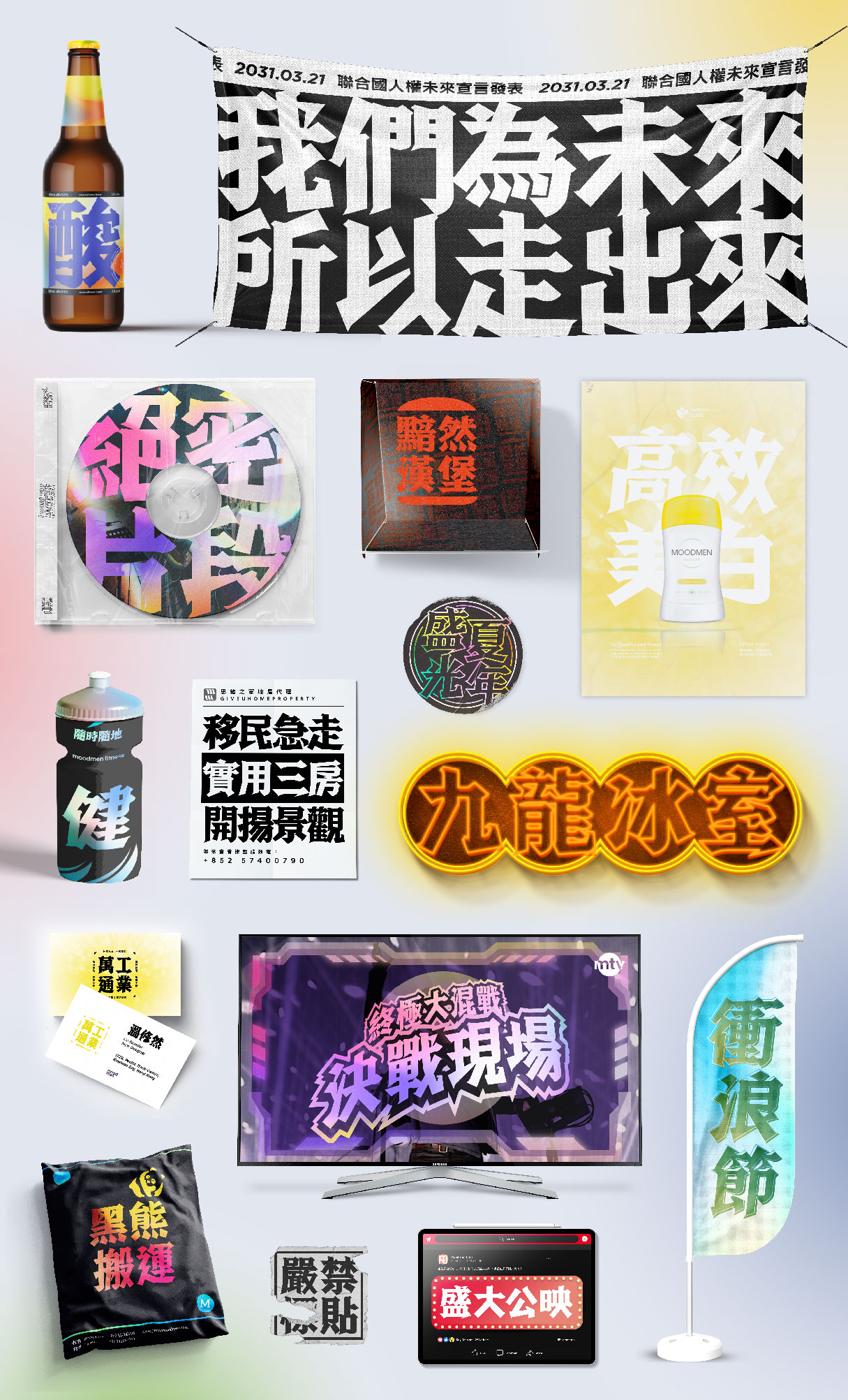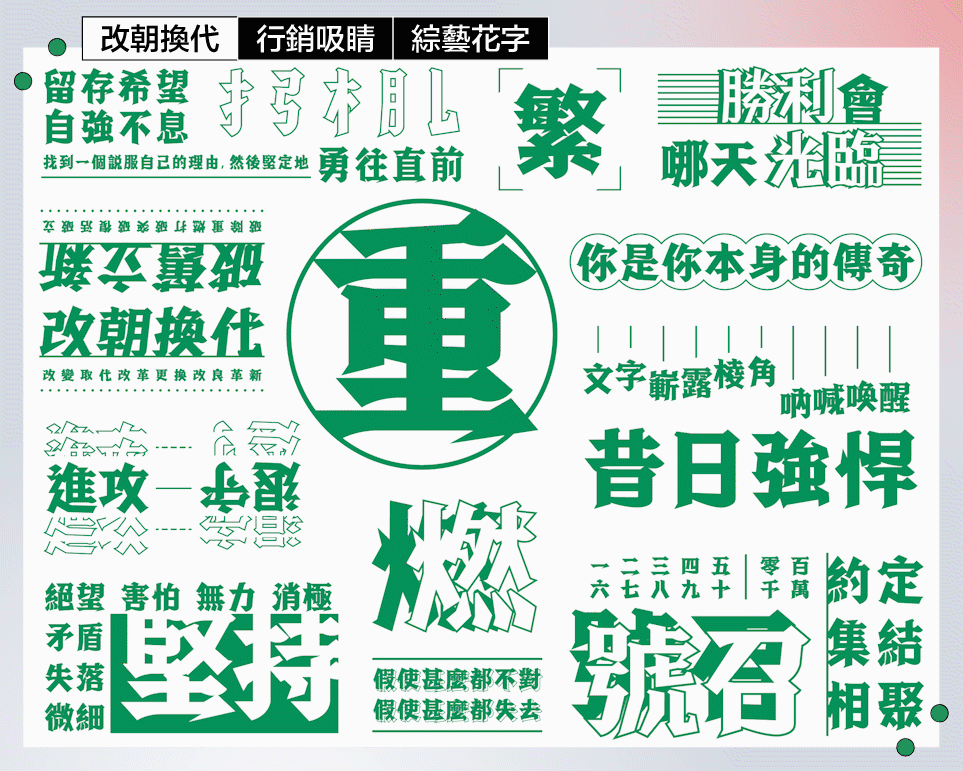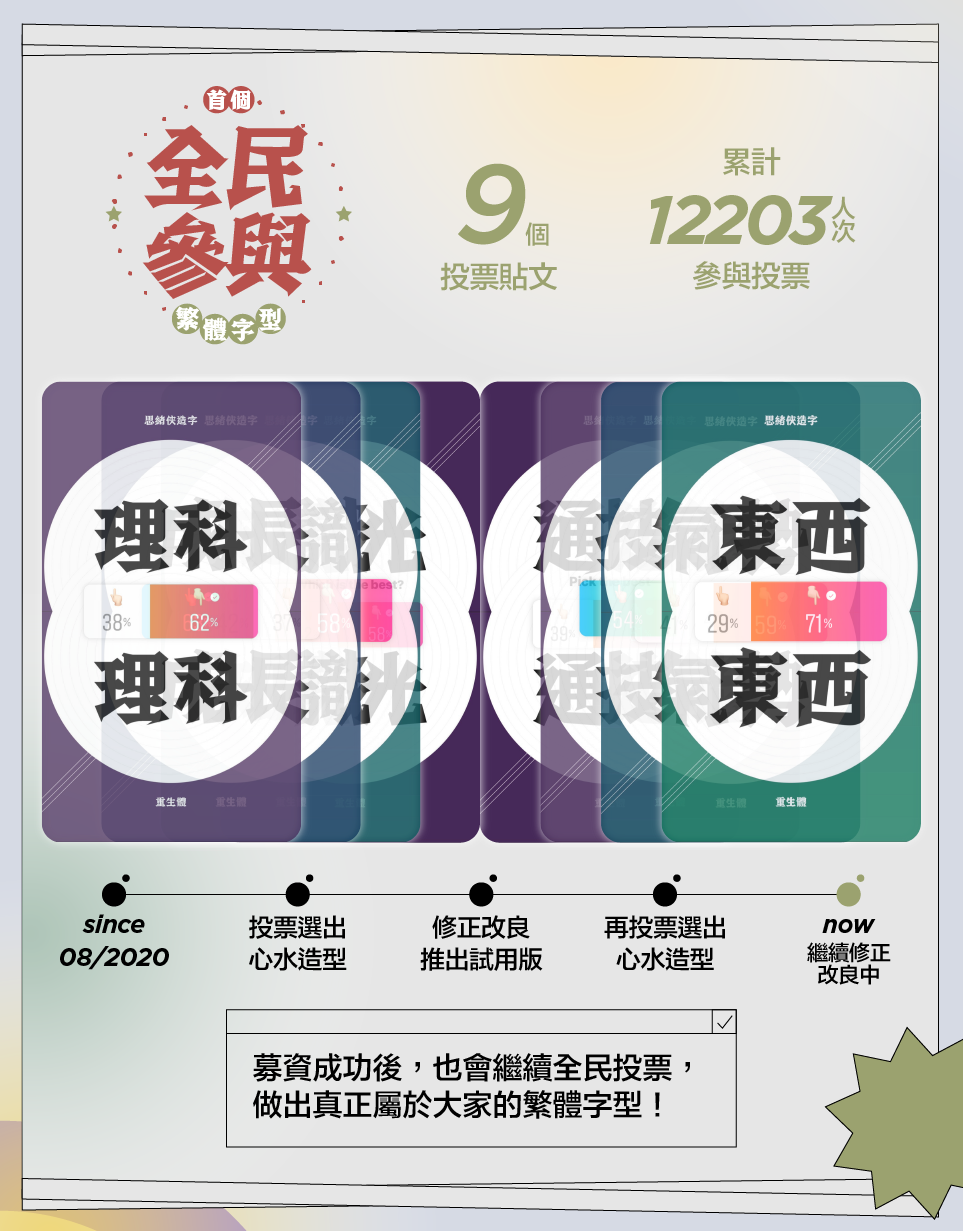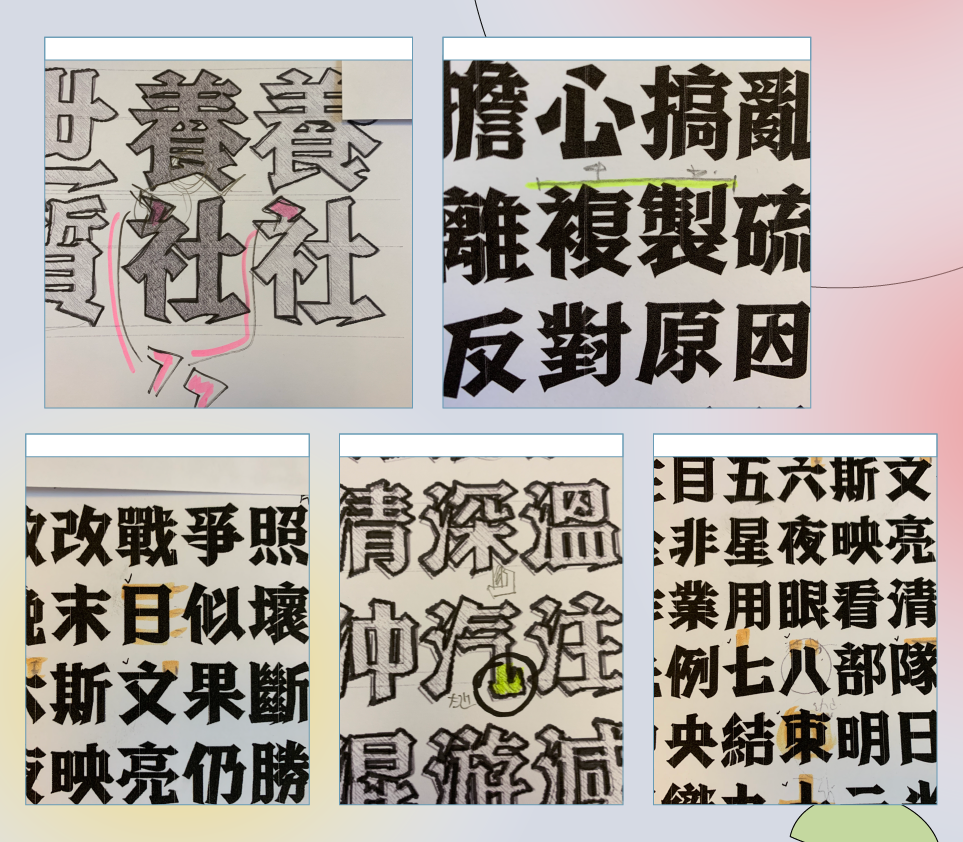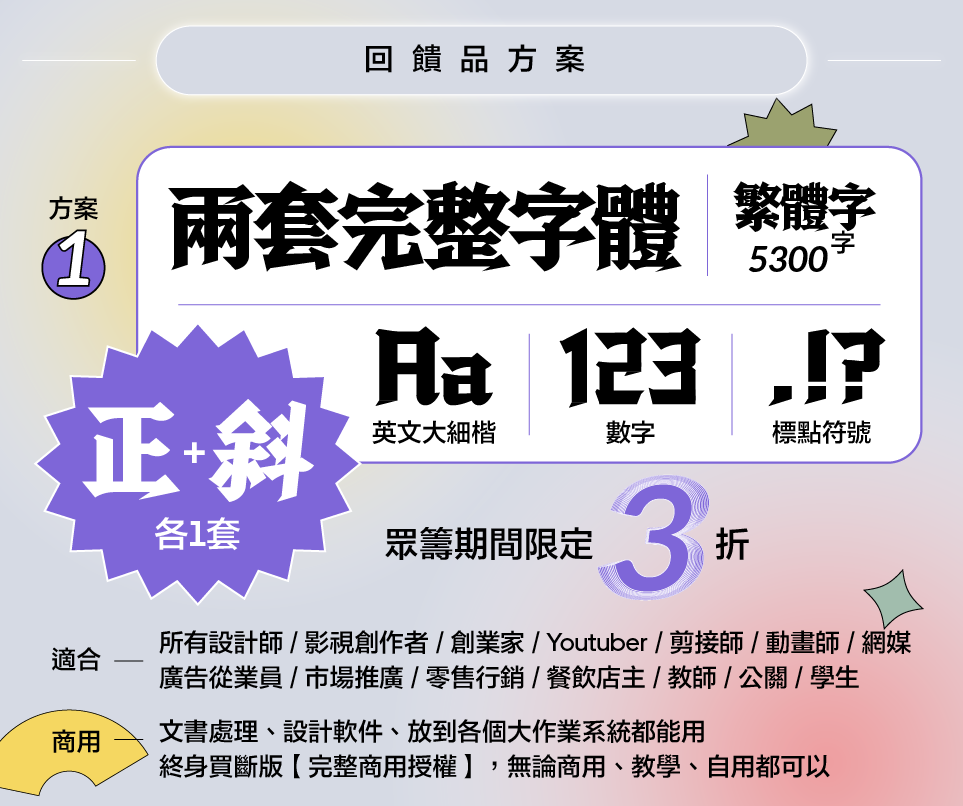
思緒重生體為思緒俠造字第一個字體項目,於2022年1月發起為期兩個月的眾籌募資,並成功募資港幣101萬(353萬台幣),會於同年12月交付5300字元版本,現時全力製作中。
在日新月異的時代洪流之中,每一個人、每一件物品彷佛都置身於記憶和遺忘之間的對奕。舊物被淘汰似乎是社會上的自然法則,但在時興復古的今天,有誰又能全盤否定它們的價值?舊事物的可愛之處,在於它從歲月之中沉澱下來的獨特韻味,不單構成了我們對這個地方的喜愛和熟悉感,同時亦為城市賦予了生命力。文化往往是能豐富一整座城市的肥料,而且正是有著這些林林總總的事物,才能堆疊出讓城市確實地文明的深度。
舊時的景物往往最具韻味,它不但是屬於香港人的回憶,更是給予這個城市個性和價值的重要角色。手雕麻雀、戲棚、點心車⋯⋯你又數得出多少曾經熟悉的事物?又有多少已經在腦海中模糊了輪廓?保育固然重要,但純粹地留住這些文化似乎還未足夠,而它們總會在某一天失傳。正因為不甘失去,香港一些日漸式微的傳統工業都嘗試以舊物為本,保留原有基礎的同時也為它注入新元素,讓它們不論軀殼還是靈魂都得以延續。
那麼,香港的文字應該傳承下去嗎?如果沒有人繼續造字,它會成為社會下一個淘汰的對象嗎?
由陳靖軒創立的思緒俠造字,自 2019 年至今透過社交平台上的字體設計作品、不同造字產品,一直致力於推廣繁體字的設計。然而,只是讓人意識到有字體設計的存在也顯然未夠,我們仍不斷在字體創作上尋求突破,才促成了思緒重生體這套完整中文字型的誕生。處於每秒都在變化的世代中,比起一味的懷舊,我們更希望在傳統的根柢上創造出與時俱進、更甚是引領潮流的一套字體。
生於複雜多變的時代中,每天都要面對著不同的變數,身邊一些珍貴而美好的事物都逐一消失。我們似乎已經對這些所謂的常態感到麻木,甚至開始默默地接受。有人說,世界上所有美好事物都會有一個期限;但我們卻不甘失去,希望可以藉著字體設計,加入一些本地獨有的人文面貌,將香港的靈魂重生。
能剛則剛,能柔則柔,做到互補之餘又恰當好處, 這就是詠春的智慧;上海理髮廳剃刀的鋒利,乾淨俐落,是對於自我肯定的表現;舞獅動作多變而威武,盡顯氣派; 手雕麻雀的精細,展現出師傅對工業的執著和熱誠。這些傳統工業雖然面臨淘汰,便仍然堅守崗位,保持應有的專業態度,若果重生體可以加入它們的元素,再將宋黑結合,我相信這將會是一套能夠延續香港靈魂的繁體字。
設計上,重生體凌厲而細緻,務求做到藝術性與可讀性之間的平衡。無論作為文案標題、招牌設計、商品包裝甚或張貼告示,重生體都能盡展其獨一無二的字體個性,為其文字內容施加張力之餘,也打破傳統字型沉實呆板的印象。尤其是在資訊爆棚的現代城市中,更需一款搶眼獨特的標題字體,留住人們的視線之後,延續他們閱讀內文的興趣。
在我們身處的後印刷時代中,印刷術極其普及的同時,電子媒介亦已融入大家的日常。重生體作為一套回應時代潮流的字體,便在字型設計的架構上揉合了印刷品慣用的「宋」和電子屏幕上常見的「黑」,讓字體靈活地配合各種應用,應對每息間千變萬化的都市。
在潮流上創新之外,重生體也希望透過宋黑結合做到文化上的傳承。宋體(明體)的歷史可追溯至古時的活字印刷,它有為了方便雕刻而加粗的豎筆和標誌性的三角裝飾,絕對稱得上傳統美學的代表。另一邊廂,黑體則是受西方字體影響才衍生出的無襯線字型,因為筆劃粗幼一致、簡明清晰,故其可塑性高也更具時代感。
重生體保留了宋體的筆劃頭尾裝飾,卻又加入了黑體的硬度、統一了橫豎筆的粗幼,從而達至宋與黑、新與舊的融合。這樣的設計除了能讓字型更獨特出眾,也令字型能廣泛應用於不同媒體、介面,呼應時代的需求。這樣一來,重生體有望能切合「加入新元素,將傳統美學轉化成潮流」這一宗旨,將固有的人文精神流傳到下一代。
重生體的橫筆是其宋體特性最濃厚的地方:它有鋼筆般銳利的開首,也有像雪糕筒的尾端裝飾,而當整個字以橫筆作結時,更有像鋤頭作出還擊的回勾。相反地,「口」字部的底部橫筆則摒棄了鋼筆和雪糕筒等裝飾換成有輕微弧度、逐漸向左收窄的回筆。如此一來,相對柔和的收筆除了能緩和視覺疲勞,也為這剛強的字體添加一點溫柔。
在其他細節設計上,重生體也十分講究,正如看似隨意的每一「點」,在不同情況下也會有各自的形狀和調整。首先在一般狀況下,點的設計會呈菱形狀並帶有尖銳的尾巴; 其次,當點作為字元尾筆或重複使用時(如在「灬」「糹」等部件中),它會順應筆劃走向調整重心並向外擴展,展現猶如書法的氣派。至於在空間不足的時候,點則會縮減至兩端收細的箭頭造型,修補正負空間的比例平衡。
此外,重生體在撇捺交叉出現的「又」字部中,會在兩筆重疊的地方隱藏一個曲折處。除了有助校正粗幼和重心,這種處理手法也讓筆劃較符合視覺上的直線,使其更順眼自然。
思緒重生體在較早前推出的試用版反應不俗,我們非常榮幸地得到各個界別的創作者支持,將重生體帶入不同作品中,當中包括由樂隊 Kolor 主理的 Ohm…cafe 內其中一個霓虹燈裝飾「醉.醒」,另外香港 Youtube channel「非實力派」亦在影片封面中使用了重生體。除了本地創作人之外,台灣餐廳「門常開合作社」的主視覺設計亦率先試用了字體。而最令我們團隊喜出望外的絕對是設計師 iohn.choi 將重生體放進作品內,並帶到了達明一派演唱會的大舞台上,我們希望藉此會有更多人認識和使用思緒重生體。
為了打造一套真正屬於香港的字體,我們進行了首個全民參與的繁體字設計項目,在埋頭苦思字體設計的同時,也希望凝聚所有熱愛繁體字的人一同參與字體的調整。我們於 2021 年 10 月推出試用版前進行了第一輪公投,挑選出部份詞彙,以同一個字、兩款不同設計的方式,讓網民進行二選一投票。我們亦跟據投票結果,在試用版出貨前作出修改,讓用家可以試用由全民參與改良所得出的字體,並回饋意見。
正正因為繁體字是大家所珍惜的,所喜愛的,才會特別著緊。我們知道當中每一筆一劃的設計都是使用者所關注的,也願意讓用家成為字體設計企劃的一份子。往後的日子在完整版還未釋出前,我們還會繼續以全民投票方式決定筆劃造型,務求盡善盡美。
如果時間是金錢的話,那麼設計繁體字便是一件非常奢侈的事。就算只以字數衡量,繁體中文的字庫已遠超於英文等語言,而且繁體字結構複雜多變,當中的每一筆一劃都是設計師需要反覆思量的學問。思緒重生體經過籌備和設計的程序後,便進入修正部分,反覆改良出至少十多個版本。我們調整的準則主要為統一直橫筆的開端、減少筆劃交集、調整比例和加強字型特性。經過三百多天反覆修正,我們不斷思考著如何才能將每一隻字都調整至最大的氣派,厚厚的一堆草圖上滿載著我們團隊對重生體的執著,以及對繁體字的熱愛。
需知道創造一個新字體的工序相當繁複,而且成本龐大,但我們還是會堅持做,除了讓大眾有多一個繁體字型的選擇之外,更是為了傳承繁體字的文化,讓香港人也會為香港製造的字體而感到驕傲!
字型選擇眾多的英文字體一般只需製作約 300 個字元,相比起來,字元總數成千上萬的繁體中文便明顯較為繁複,也自然要耗費更多時間心力。跟據台灣教育部所編訂的中文字編碼庫,電腦中常用的繁體字共有 13,051 個,並可劃分為 5,401 個「最常用字」及 7,650 個「次常用字」。因此,一套完整中文字型動輒便需花上以年計的時間去完成,而這也是市面上繁體字型少之又少的主因。
據統計,1,000 個常用中文字其實已覆蓋了 92% 的書面資料,3,000 個常用字更能達到 99% 的覆蓋率。早前,思緒重生體已從最常用字中精選了「表演」、「勝利」等 1,000 個「超常用字」作為試用版率先釋出。在眾籌第一階段中我們會加入「搜索」、「巔跛」等補至一共 5,300 個字元,當中亦包括「冇乜」、「佢哋」等香港常見字。雖然 5,300 字已能應付近乎全部設計上所需的文字,然而也有唏噓的「唏」、叱咤的「咤」等不屬最常用字、卻偶爾會用上的缺字,仍有待眾籌第二階段的 8,800 字去解鎖。要讓思緒重生體成為一套完整的字體,我們需要你的支持, 讓世界知道香港製造的字體是有市場、有品質及有價值的。
【回饋方案一】為是次眾籌的主打,我們將會提供正斜體各一套的思緒重生體。作為一套香港製造的繁體字,除了英文大細階、數字和基本的標點符號之外,重點一提的是,在 5,300 個繁體字當中也包括了一些香港口語字(例如「佢」、「啲」、「咁」、「嗰」、「係」等) 方便香港人使用。正體方面我們著手調整字體結構的比例,而斜體我們亦反覆比對不同斜度,最後選出了最為適合的 6°,希望可以節省使用者自行調整的時間。為了回饋支持者,整套字體於眾籌期間將會以限定 3 折出售!
【回饋方案二】思緒重生體將會首次出售眾籌限定的麻雀套裝。麻雀以藍黃橙三色設計,外觀新穎時尚,期望傳統麻雀耍樂的聯誼活動得以承傳,也拉近人與人之間的關係。
【回饋方案三】為重生體文具套裝,當中包括織章、貼紙、杯墊和掛飾,適合所有支持重生體和熱愛繁體字的人。
思緒重生體由 2020 年開始籌備,從設計初稿到暫名,到 2021 年開始投入製作,經過多次調整以及拼字測試的工序,製作了長達一年半的時間後,於上年十月公開發售千字試用版。2022 年 1 月眾籌募資正式上線,但此階段只為項目的開端,隨後我們團隊將會全程投入開始製作 5,300 字元的版本,並隨著募資進程而製作合共 8,800 個字元及其餘字重。希望大家繼續支持是次眾籌項目,讓思緒重生體得以實現。
思緒俠造字誕生於 2019 年的機緣巧合之下,由一份造字月曆開始,純粹地以文字和設計扣動眾人心弦。在社交媒體平台上分享造字作品,將字體設計融入開瓶器、浮字機殼等不同產品之中,只為了讓大家知道:「原來,香港也有字體設計。」字體設計不複雜,它可以是設計師為了配合設計而對原有字體作出的微調;字體設計不簡單,它可以是設計師反覆鑽研雕琢多時的心血。但其實,字體也無異於其他設計,一樣有它自身的價值,一樣值得大家的重視。
香港的字體設計未算蓬勃,而思緒重生體選擇在這地這刻萌芽,可說是一場試驗、一場挑戰。除了想喚醒某些日漸褪色的香港文化,重生體還肩負了一個使命——教育人們付費使用字體和版權教育。繁體字的一撇一捺都異常講究,要開發一套完整的字體更需要大量的人力物力,因此也極其需要大眾的支持。雖然在創作過程中面對著不少的困難和無力感,但非常感激各界一路相伴攙扶,無形中推動了重生體的進程。思緒重生體只是一個起步。若果眾籌計劃有幸成功,相信將來也會有更多「思緒」系列字體陸續面世。孤掌難鳴,唯望設計師看到重生體成功的步伐,吸引更多人入職字體設計,慢慢在香港形成行業,一起壯大「香港設計」這個品牌。